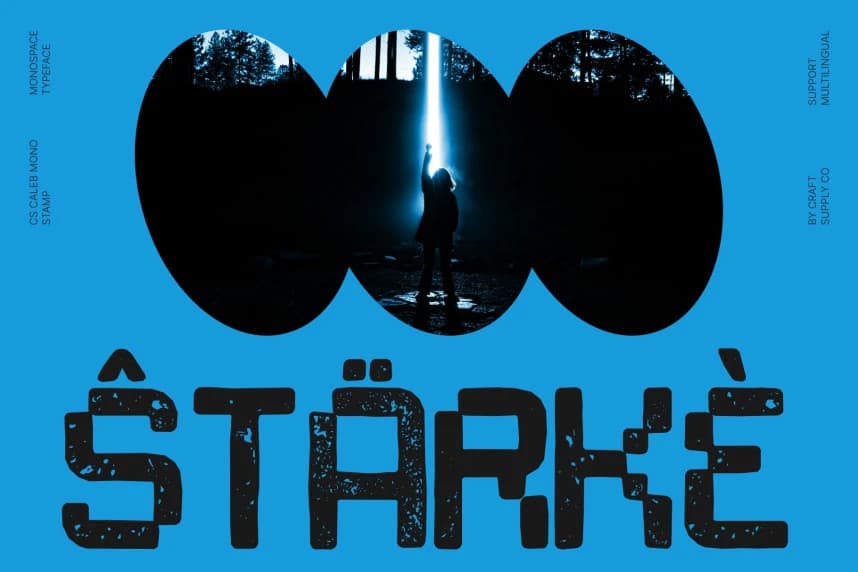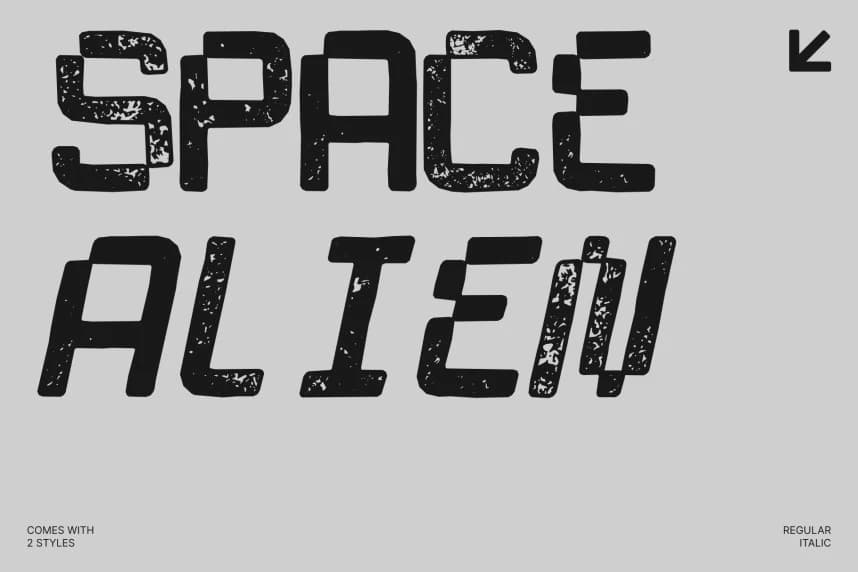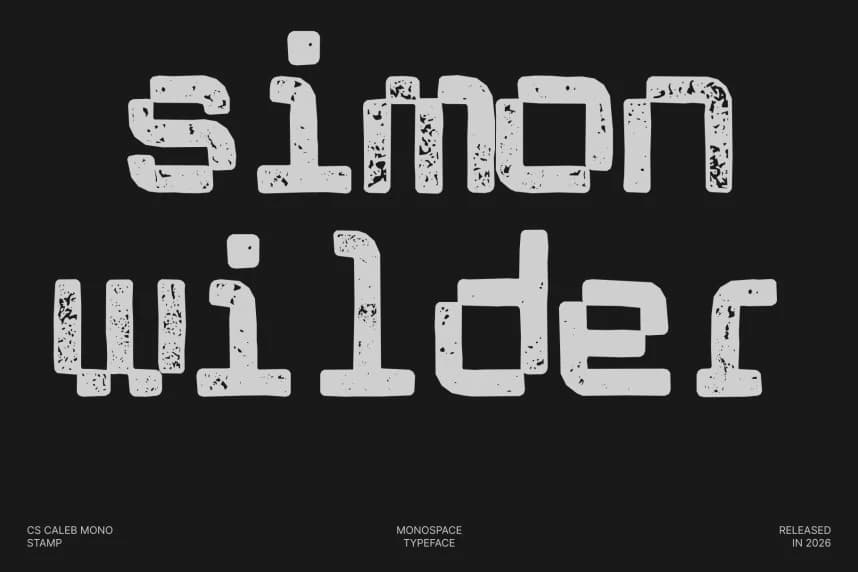
CS Caleb Mono Stamp Font
CS Caleb Mono Stamp Font – Monospaced Display Font with Retro Stamp Texture. Yapısal Kesinlik, El Yapımı Karakterle Buluşuyor. Bu damga, monospace yazı tipinin netliğini, vintage damga etkisinin dokunsal çekiciliğiyle bir araya getirir.
CS Caleb Mono Stamp Font – Monospaced Gösterim Yazı Tipi, Retro Damga Dokusu ile Yapısal Keskinliğin El Yapımı Karakterle Buluşması. Bu Damga, monospaced bir yazı tipinin netliğini, vintage damga etkisinin dokunsal çekiciliğiyle birleştiriyor.